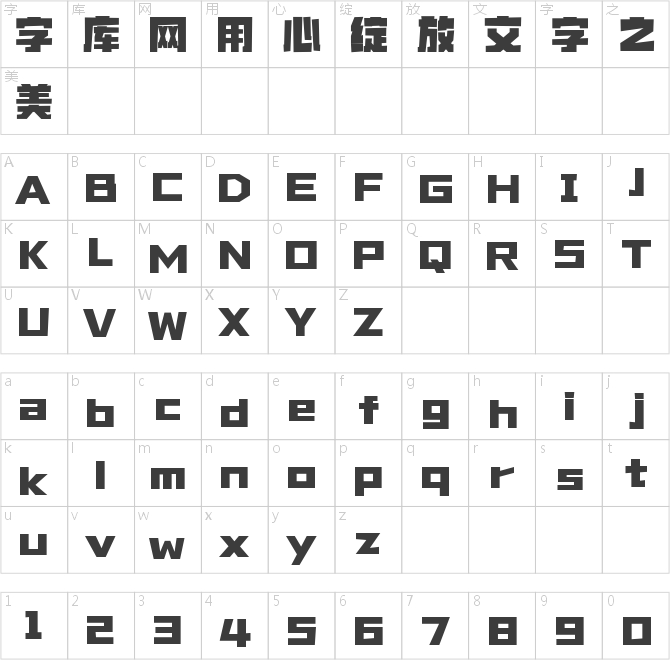
山海機(jī)甲粗黑
山海機(jī)甲粗黑,是一款綜藝標(biāo)題黑體字體,包含簡體漢字6763個。該字體是一款具有強(qiáng)勁視覺沖擊力的綜藝風(fēng)格標(biāo)題字體。字形充實(shí)填滿整個字框,造型硬朗,全直線的筆畫構(gòu)成棱角分明、堅(jiān)實(shí)有力。